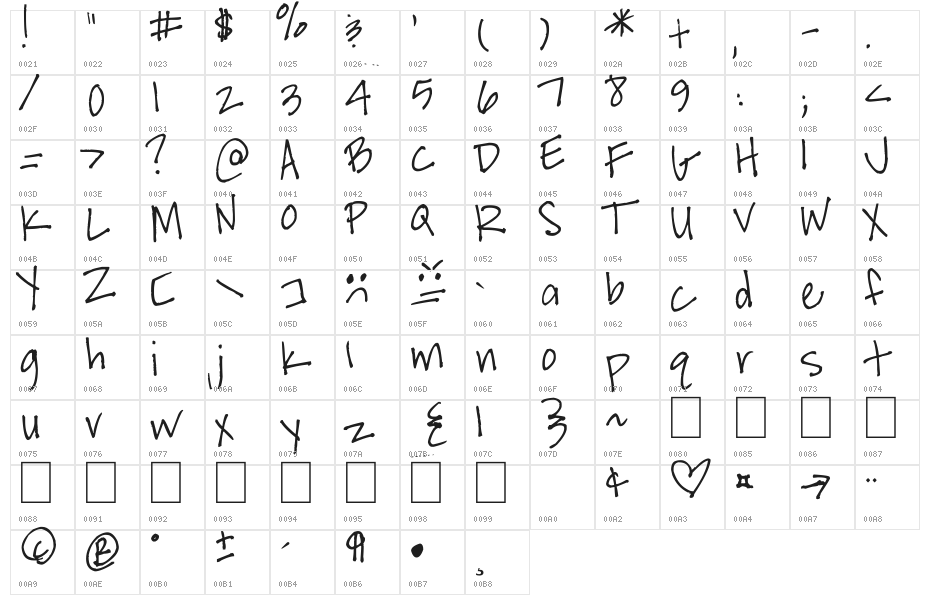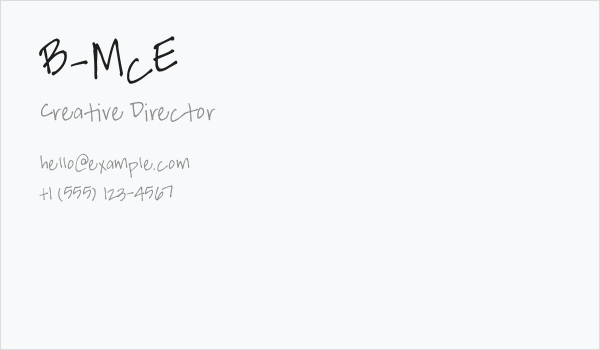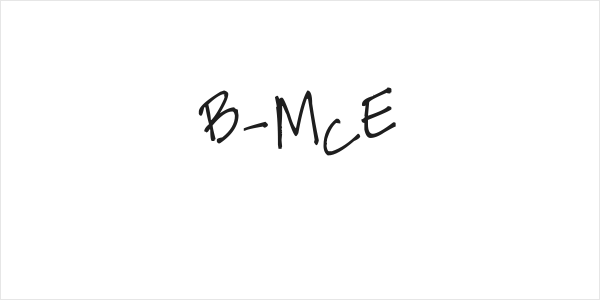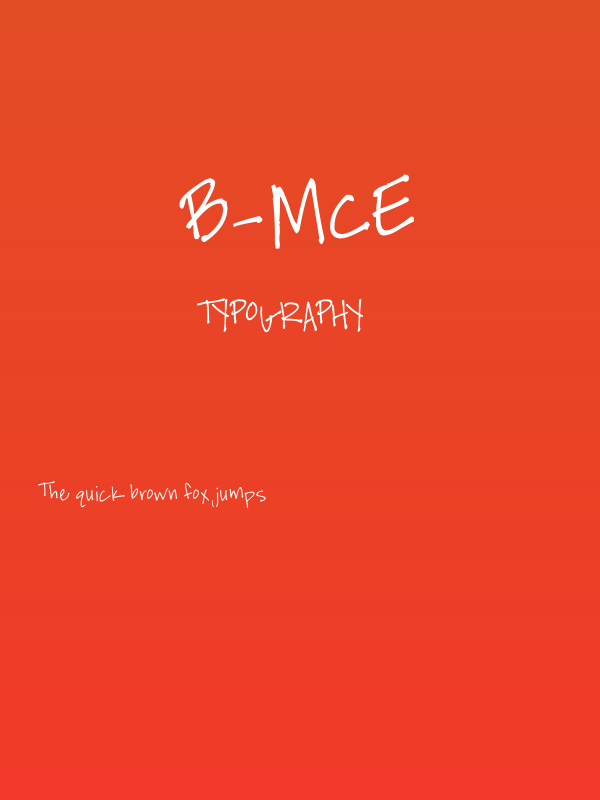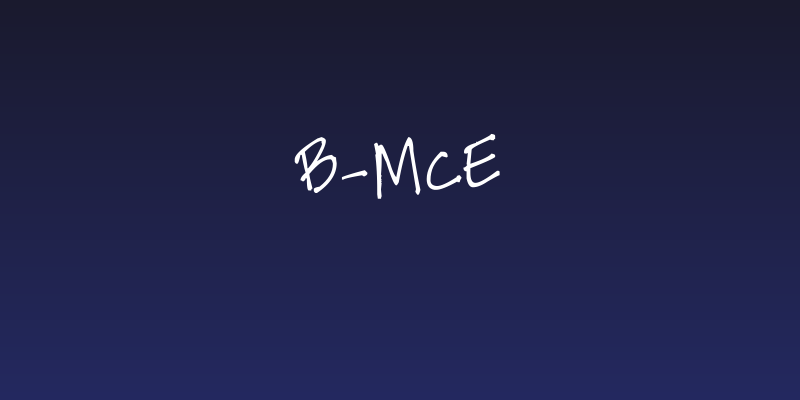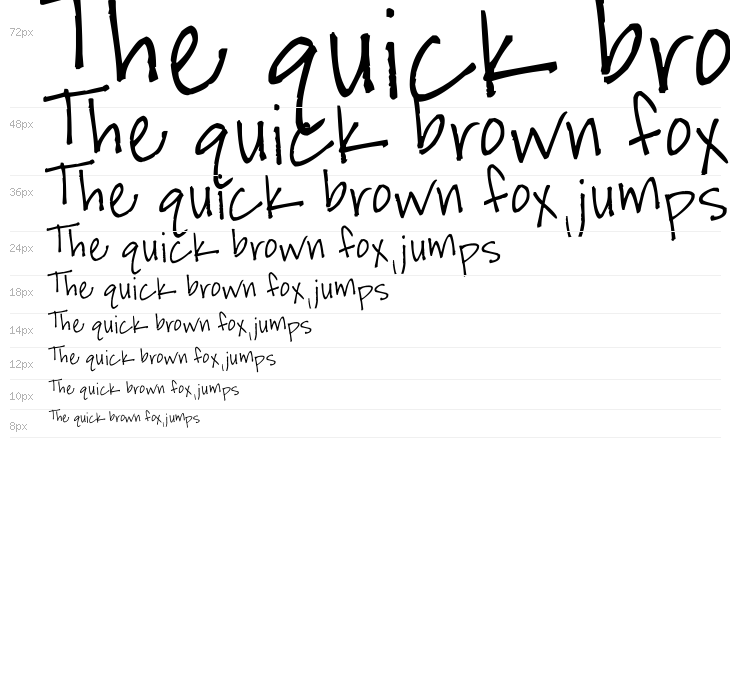
B-McE Font
| Stile generale | Casual, Playful |
| Caso d'uso | Headlines, Informal text, Creative projects |
| Progetti proposti | Ideal for greeting cards, personal blogs, creative projects, and informal branding. |
B-McE